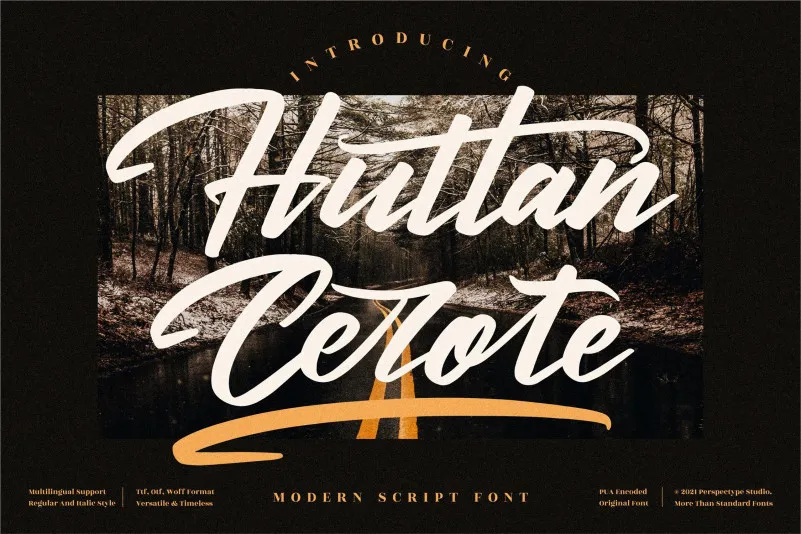
Huttan Cerote Font – Fonte Grátis
Huttan Cerote Font
Esta é uma fonte cíliada que transmite modernidade e boldness. Perspectype criou-a pensando no ato de personalizar, ideal para designs que precisam de um estilo único como convites de casamento, cartões de agradecimento, cartas de cumprimentos, logotipos ou qualquer outro tipo de projeto onde uma gravação personalizada faça toda a diferença. Perfeita para quem busca uma fonte que oferece um grande leque de opções em termos de cílios e variações chamadas swashes, sem qualquer esforço. O fato de ser PUA encodada significa que você pode acessar todas as letras e cílios desta fonte facilmente. É perfeitamente adaptável para vários estilos de design, tornando-a uma escolha ótima tanto para iniciantes quanto para designers experientes.